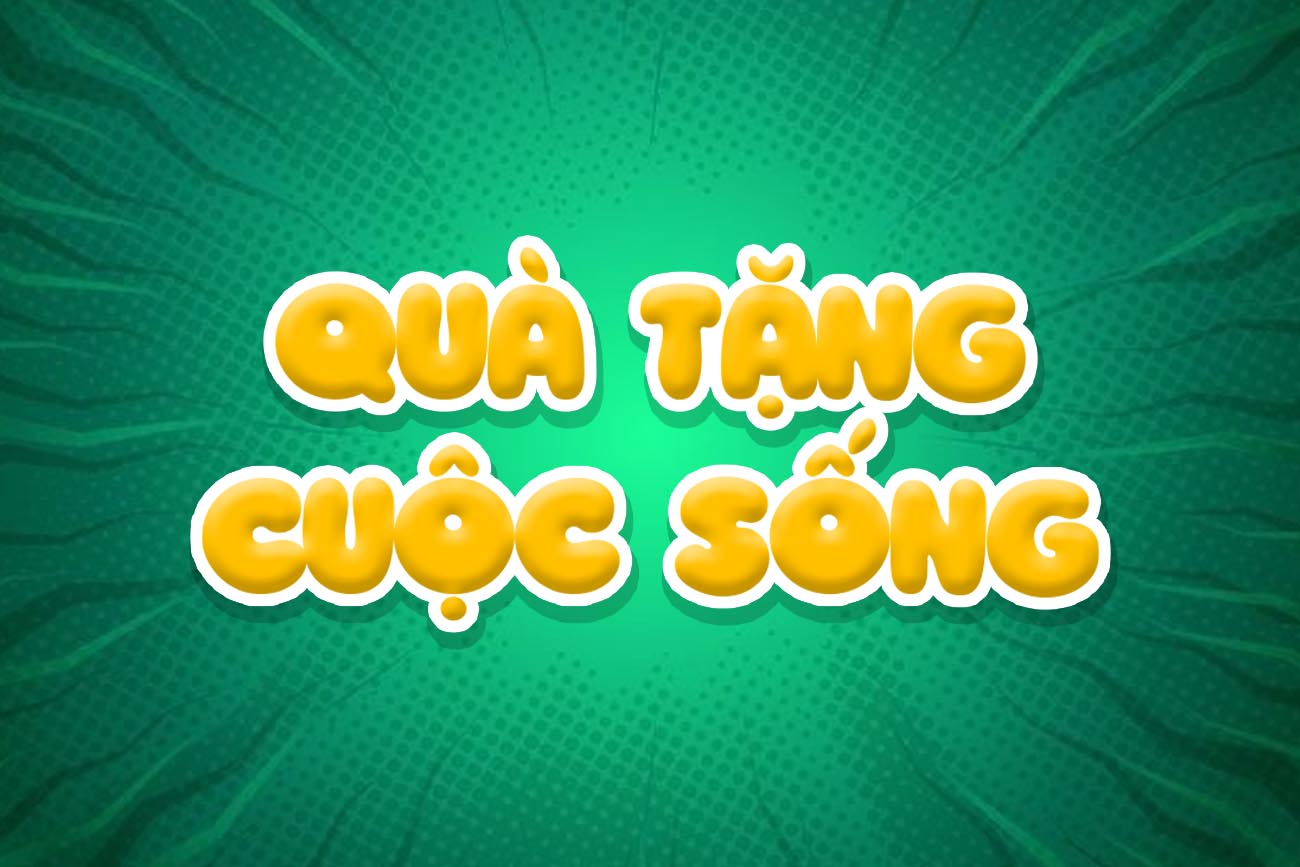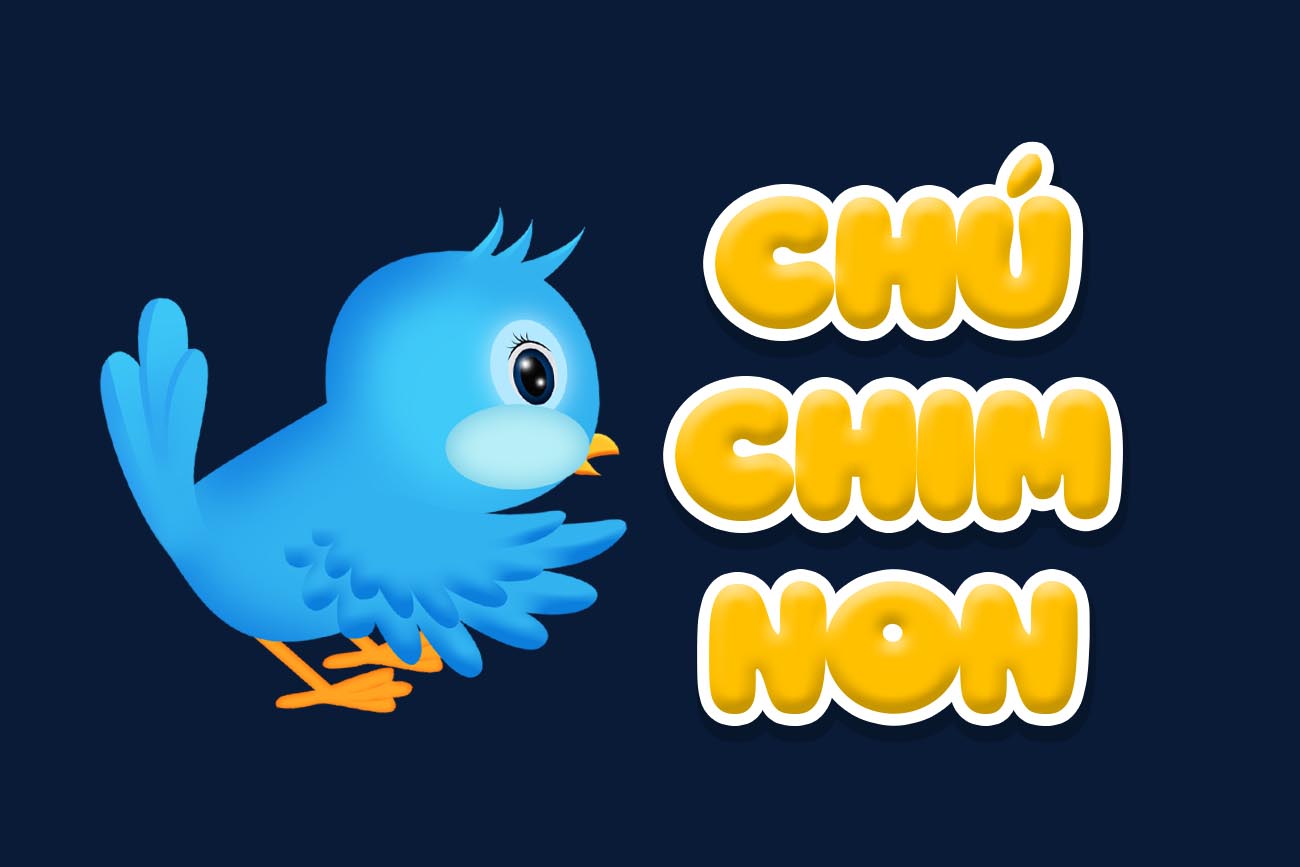
Tác giả Hanoded
Việt hóa Team SVN
Bạn đang tìm một font chữ hoạt hình Việt hóa mang phong cách vui tươi, đáng yêu và phù hợp với các thiết kế dành cho trẻ nhỏ? SVN Ziclets chính là lựa chọn lý tưởng giúp bạn tạo nên những ấn phẩm rực rỡ sắc màu và tràn đầy năng lượng tích cực.
Kiểu dáng béo tròn, dễ thương và đầy cá tính
SVN Ziclets là một font chữ ngộ nghĩnh với tạo hình béo tròn, mềm mại và tinh nghịch. Các chữ cái được thiết kế như thể được vẽ tay bằng bút dạ, tạo cảm giác gần gũi, thân thiện. Font đặc biệt phù hợp với các thiết kế mang tính vui nhộn như:
• Poster hoạt hình
• Bao bì đồ chơi, sản phẩm cho bé
• Banner trường mầm non, lớp mẫu giáo
• Sách ảnh, truyện tranh thiếu nhi
Không chỉ đơn thuần là một font chữ dễ thương, SVN Ziclets còn sở hữu nét phá cách riêng nhờ tỷ lệ chữ hơi phình to, các đường bo tròn tự nhiên, giúp mỗi thiết kế trở nên sinh động và nổi bật ngay từ ánh nhìn đầu tiên.
Việt hóa đầy đủ, hỗ trợ tiếng Việt không lỗi dấu
Nguồn gốc font và chất lượng chuyên nghiệp
SVN Ziclets có nguồn gốc từ bộ font Ziclets nổi tiếng do Comicraft – một studio chuyên thiết kế font cho truyện tranh và phim hoạt hình – sáng tạo. Font được thiết kế theo tiêu chuẩn chất lượng quốc tế, đảm bảo tính thẩm mỹ, cân đối, và dễ đọc trên nhiều kích cỡ màn hình, ấn phẩm in ấn hoặc kỹ thuật số.
Phiên bản Việt hóa do Font SVN phân phối giữ nguyên tinh thần gốc của font, đồng thời bổ sung đầy đủ ký tự tiếng Việt, tạo nên sự kết hợp hoàn hảo giữa quốc tế và bản địa.
SVN Ziclets không chỉ là một font chữ béo tròn đáng yêu, mà còn là một công cụ sáng tạo đầy cảm hứng dành cho các nhà thiết kế theo đuổi phong cách vui nhộn, ngộ nghĩnh và trẻ trung. Nếu bạn đang làm việc với các dự án hướng đến trẻ em hoặc cần một chút màu sắc tinh nghịch cho sản phẩm của mình, đừng bỏ qua font chữ đặc biệt này!